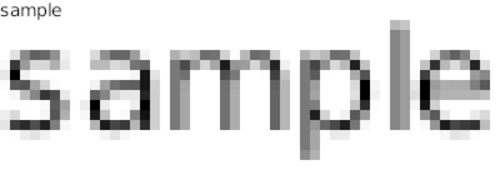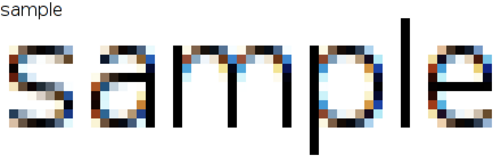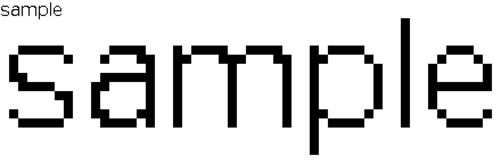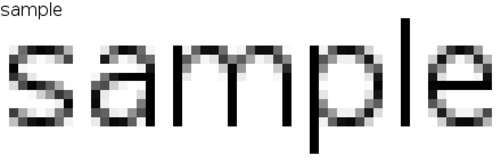
upright=乗数を から に1.70わずかに変更するだけ1.75で、大きく異なるレンダリング異常が発生します。これは、整数フォントサイズの使用による丸め誤差が原因であると考えられます。フォントのラスタライズとは、ベクター形式のテキスト記述( TrueTypeフォントなどのスケーラブルフォントに含まれるもの)をラスター形式またはビットマップ形式に 変換するプロセスです。このプロセスでは、画面上のテキストをより滑らかで読みやすくするために、アンチエイリアシング処理が行われることがよくあります。また、特定の文字サイズに合わせてレンダリングの詳細を最適化するためにフォントデータに埋め込まれた情報であるヒンティング処理が含まれる場合もあります。
ラスタライズの最も単純な形式は、アンチエイリアシングを一切使用しない単純な線描画です。マイクロソフトの用語では、これは二値(より一般的には「白黒」)レンダリングと呼ばれ、グリフを描画するために中間色(グレー)は使用されません。(実際には、任意の 2 色を前景と背景として使用できます。)[ 1 ]この形式のレンダリングは、エイリアスまたは「ギザギザ」とも呼ばれます。[ 2 ]これは、計算負荷が最も少ないという意味で、最も高速なレンダリング方法です。ただし、レンダリングされたグリフが小さなサイズで解像度を失い、認識しにくくなる可能性があるという欠点があります。そのため、多くのフォントデータファイル(TrueType など)には、ラスタライザーがグリフの特に問題のある領域のピクセルをどこにレンダリングするかを決定するのに役立つヒント、または特定のピクセルサイズで使用するために手動で調整されたビットマップのセットが含まれています。[ 1 ]典型的な例として、Windows 95より前のすべてのバージョンのMicrosoft Windows ( Windows 3.1など) は、このタイプの組み込みラスタライザーのみを提供していました。[ 2 ]
より複雑なアプローチとしては、コンピュータグラフィックスの標準的なアンチエイリアシング技術を用いる方法があります。これは、文字の端にある各ピクセルについて、文字がそのピクセルのどの部分を占めているかを判断し、そのピクセルをその不透明度で描画すると考えることができます。例えば、白(FFFFFF)の背景に黒(000000)の文字を描画する場合、ピクセルが理想的には半分塗りつぶされるべき場合(例えば、角から角への対角線で)、そのピクセルは50%グレー(BCBCBC)で描画されます。この手順を単純に適用しすぎると、文字がぼやけてしまうことがあります。例えば、文字に1ピクセル幅であるべき垂直線が含まれているにもかかわらず、それがちょうど2つのピクセルの間にある場合、画面上では2ピクセル幅のグレーの線として表示されます。このぼやけは、鮮明さを犠牲にして正確さを犠牲にしています。しかし、現代のシステムでは、多くの場合、線が整数ピクセル座標内に収まるように強制されるため、文字はより鮮明に見えますが、印刷された紙に描かれた場合よりも線がわずかに太くなったり細くなったりします。
ほとんどのコンピュータディスプレイは、複数のサブピクセル(通常は赤、緑、青それぞれに1つずつ、これらを組み合わせて全色を表現)で構成されたピクセルを持っています。フラットパネルディスプレイなどでは、ピクセル全体を使用するのではなく、サブピクセル解像度でレンダリングすることで、画面の実効解像度を高めることが可能です。これは一般にサブピクセルレンダリングと呼ばれています。サブピクセルレンダリングの独自実装の1つとして、マイクロソフトのClearTypeがあります。
現代のオペレーティングシステムでは、ラスタライズ処理は通常、多くのアプリケーションで共通して使用される共有ライブラリによって提供されます。このような共有ライブラリは、オペレーティングシステムやデスクトップ環境に組み込まれている場合もあれば、後から追加される場合もあります。原則として、各アプリケーションは異なるフォントラスタライズライブラリを使用できますが、実際にはほとんどのシステムが単一のライブラリに標準化しようとしています。
Microsoft Windows はWindows XP以降、サブピクセル レンダリングをサポートしています。一方、ClearType を使用しない標準の Microsoft ラスタライザーは、タイプ デザイナーの明瞭さの意図を優先する例です。タイプ デザイナーのヒンティングの意図に従ってテキストを整数座標位置に強制し、タイプデザイナーのガスプ テーブルの意図に従って特定のサイズの特定のフォントにアンチエイリアスを適用しないことで、画面上では読みやすくなりますが、印刷すると多少異なって見える場合があります。これは、Windows 7 および Windows Vista プラットフォーム アップデートで Direct2D/DirectWrite が出荷されたことで変更され、1/16 ピクセル サイズまでのサブピクセル テキスト配置が可能になりました。[ 3 ]
Mac OS XのQuartz は、サブピクセル位置決めを使用しているのが特徴です。グリフを正確なピクセル位置に強制するのではなく、サブピクセル レンダリングを含むさまざまなアンチエイリアシング技術[ 4 ]を使用して、文字や行をタイプ デザイナーの意図したヒントから遠ざかり、元のアウトラインに近づけるように配置します。その結果、画面上の表示は印刷出力と非常によく似ていますが、小さなポイント サイズでは読みにくい場合があります。Quartz レンダラーは、macOS Mojave 以降、サブピクセル レンダリングを削除し、代わりにグレースケール アンチエイリアシングのみに依存するようになりました。この変更は HiDPI の「Retina」スクリーンでは許容範囲内ですが、外部モニター上のテキストは読みにくくなります。[ 5 ]
他のほとんどのシステムはFreeTypeライブラリを使用しており、設定によってはMicrosoftとAppleの実装の中間に位置する可能性があります。FreeTypeはヒンティングとアンチエイリアシングをサポートし、オプションでサブピクセルレンダリングと位置決めを実行します。FreeTypeは、カラーバランスの取れたサブピクセルレンダリングやガンマ補正など、どちらの実装にも存在しない機能も提供します。[ 6 ]
アプリケーションによっては、独自のフォントレンダリングソリューションを持ち込む場合もあります。Skia Graphics Engine ( Google Chromeで使用されている) のようなグラフィックスフレームワークは、独自のフォントレンダラーを使用することがあります。ビデオゲームやその他の 3D アプリケーションでは、さまざまなSDFベースのレンダラーや「Slug」などの、より高速な GPU ベースのレンダラーが必要になる場合もあります。[ 7 ]